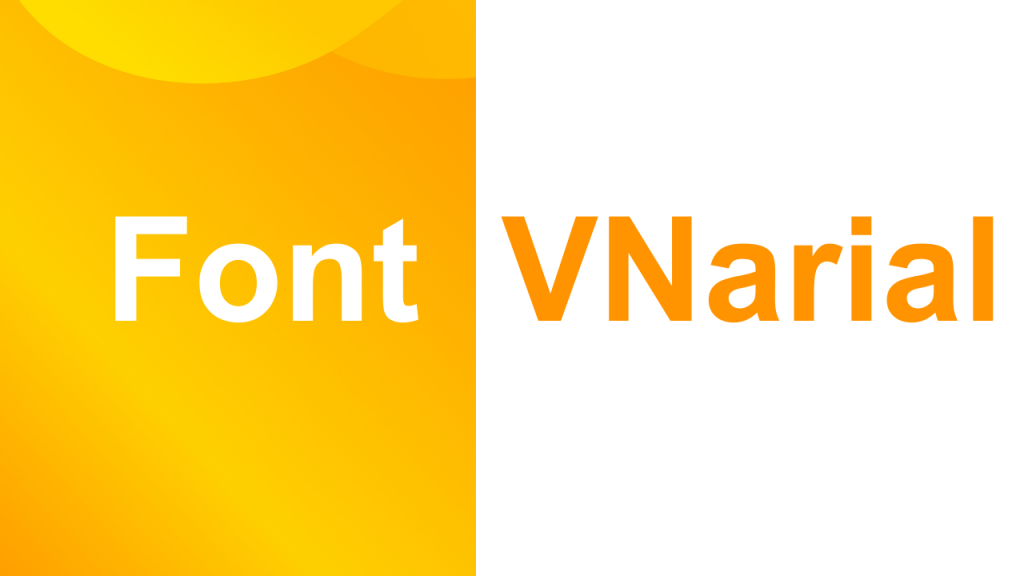
Font VNI VNarial
Ngôn ngữ: Tiếng Việt, Tiếng Anh
Bộ Font: Font VNI
Font VNI VNarial là một trong những phông chữ quen thuộc đối với người dùng tại Việt Nam, đặc biệt là trong các tài liệu văn phòng và thiết kế đồ họa. Với thiết kế đơn giản nhưng tinh tế thuộc bộ font chữ không chân nên Font VNI VNarial mang lại sự dễ đọc và thẩm mỹ cao cho văn bản, đồng thời hỗ trợ đầy đủ các ký tự tiếng Việt. Phông chữ này không chỉ phù hợp với các ứng văn bản như Word hay Excel mà còn được sử dụng rộng rãi trong các phần mềm thiết kế như Photoshop hay Illustrator, giúp người dùng dễ dàng tạo ra những sản phẩm chuyên nghiệp và hấp dẫn.